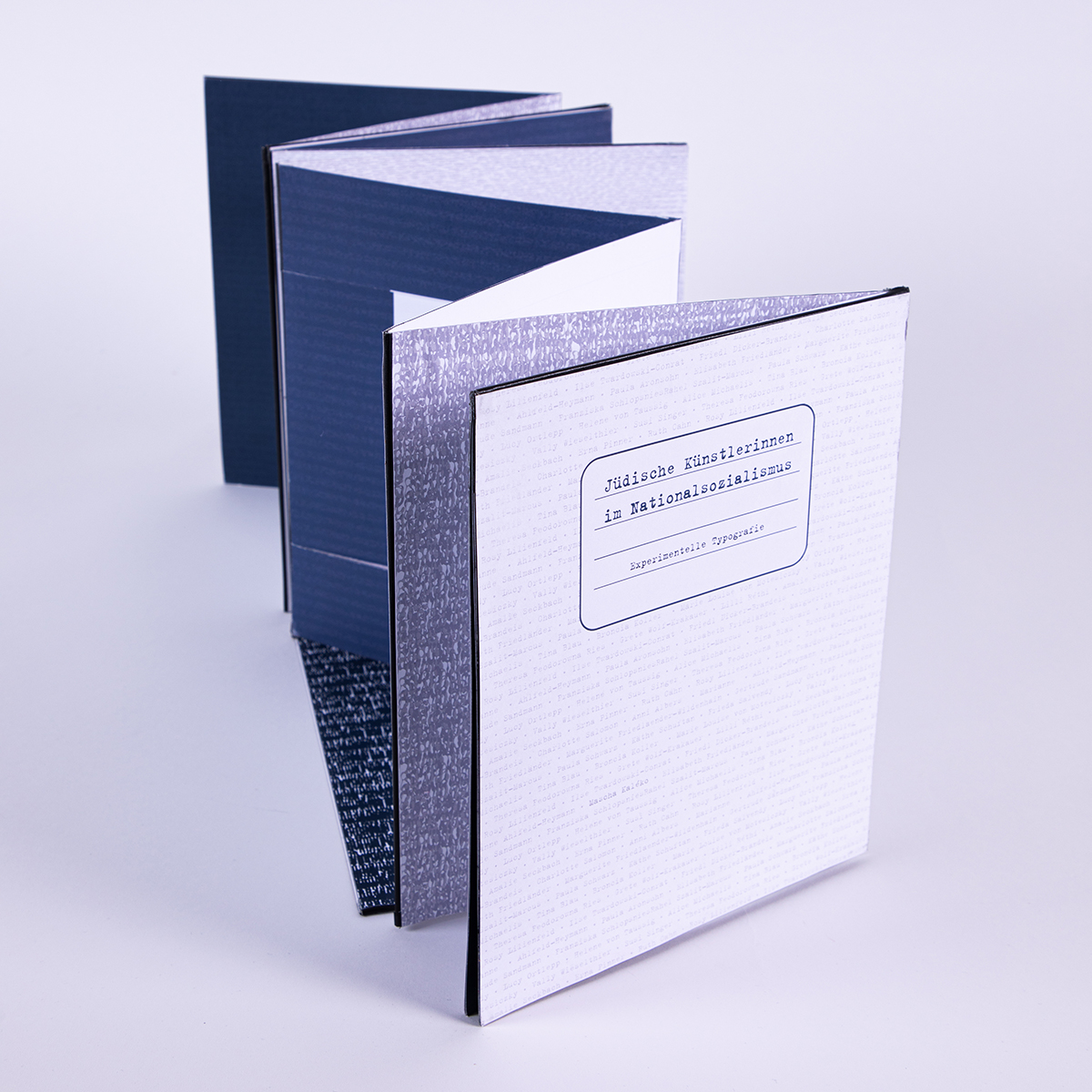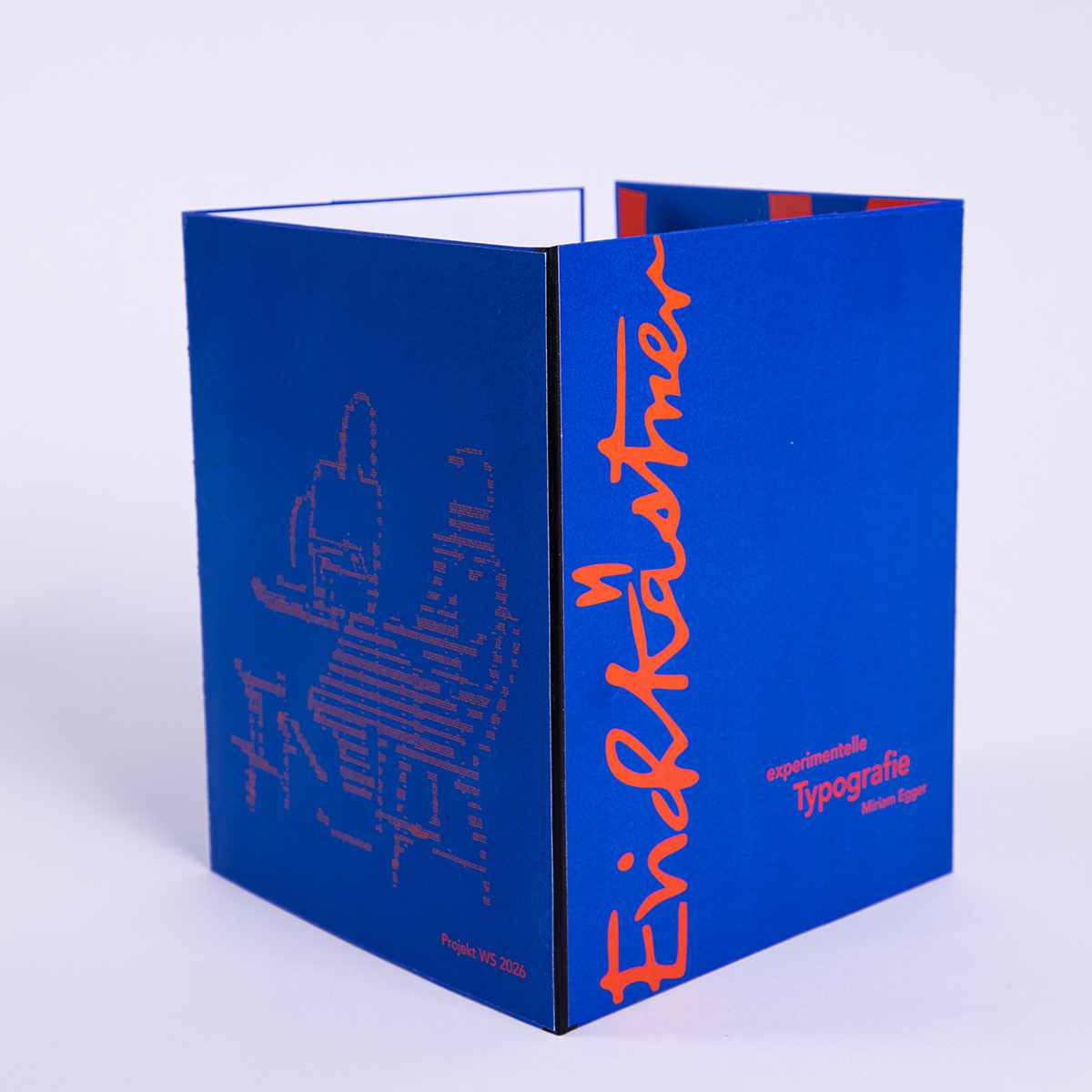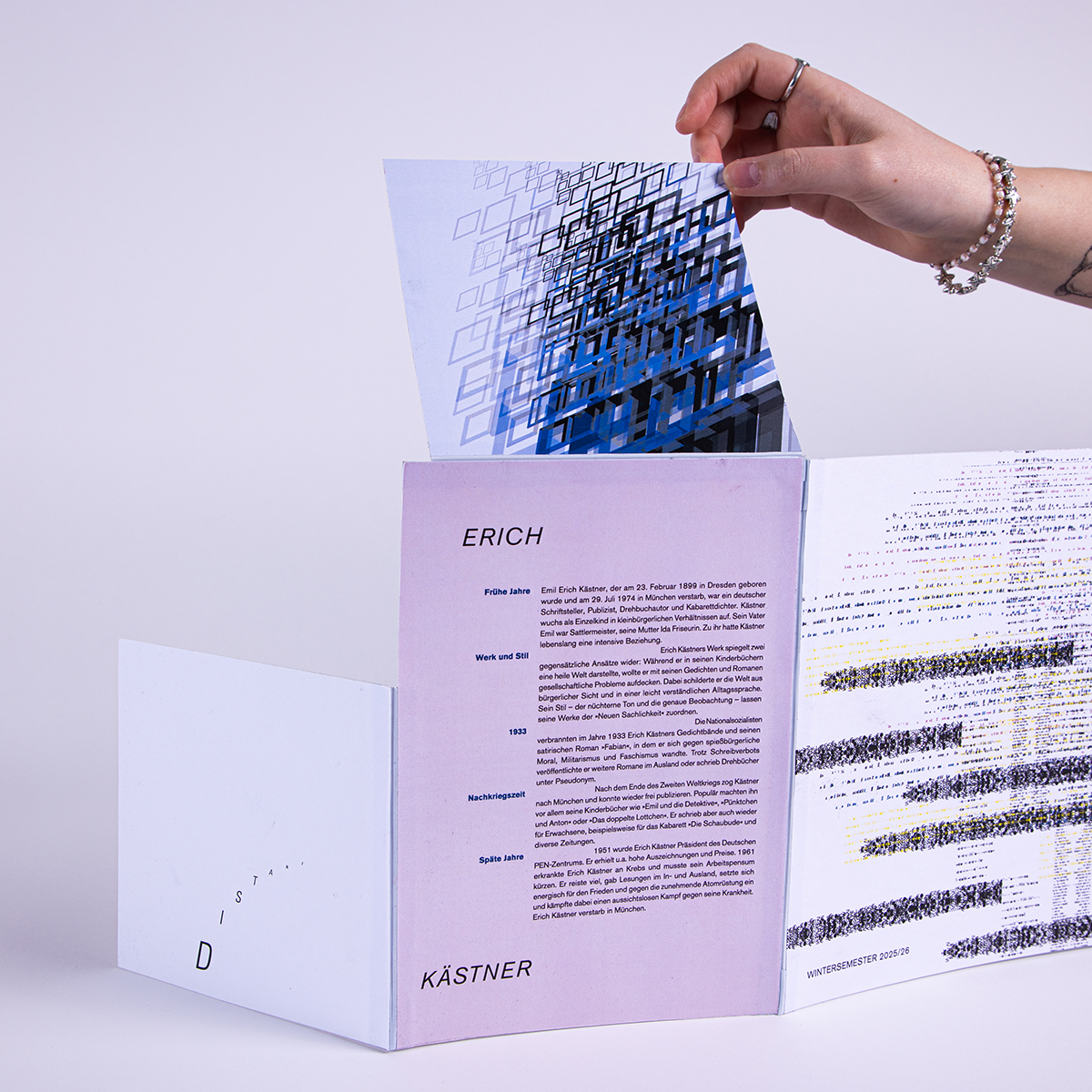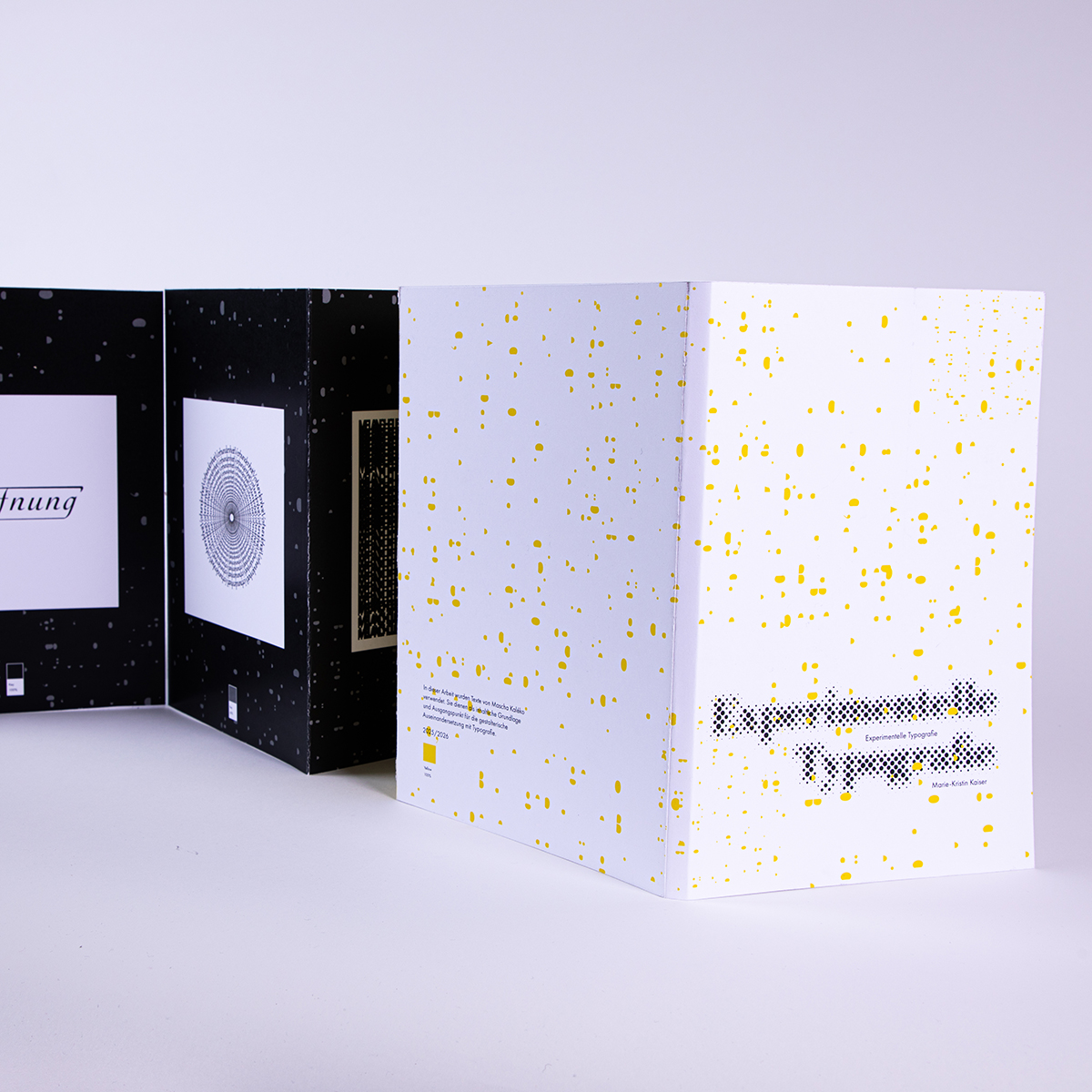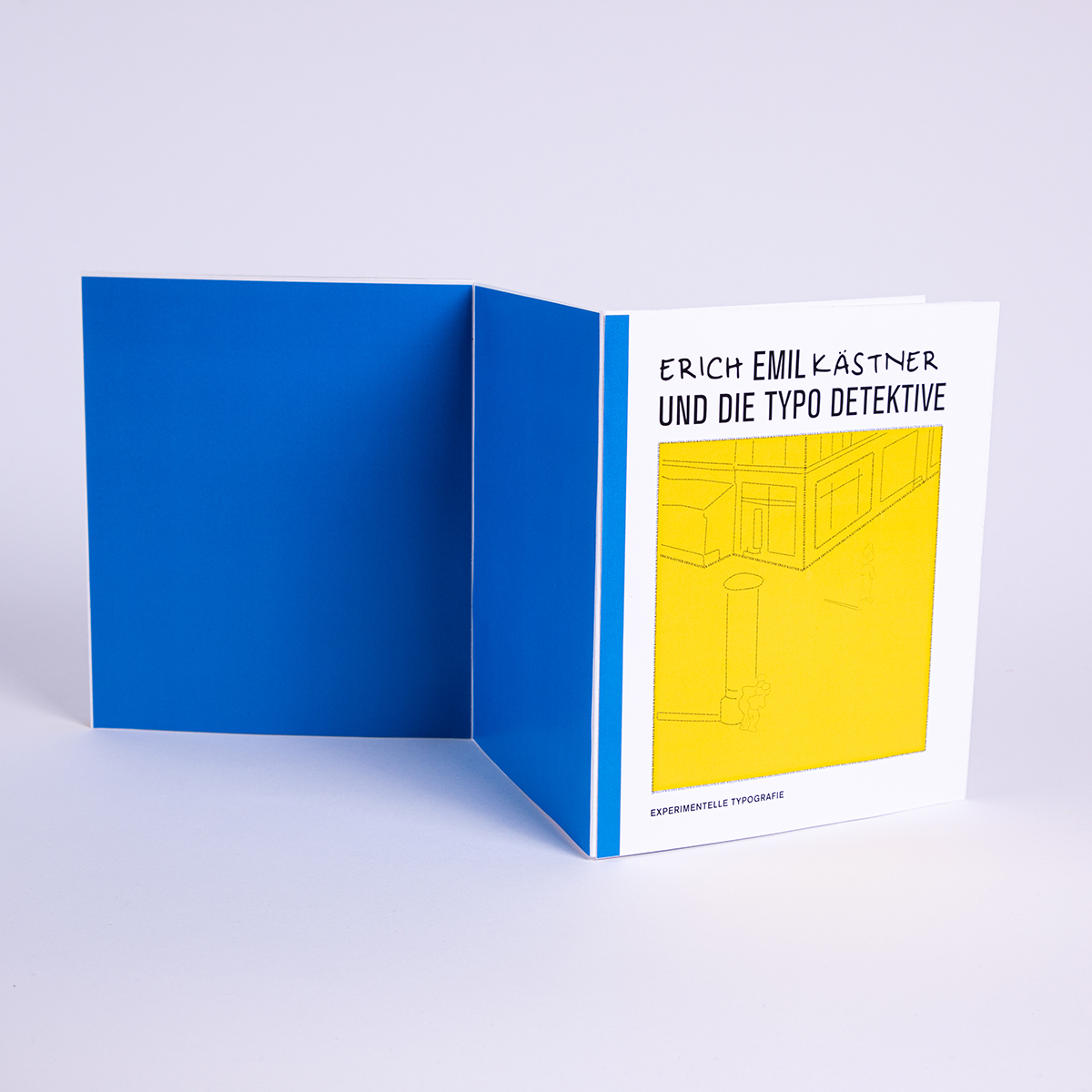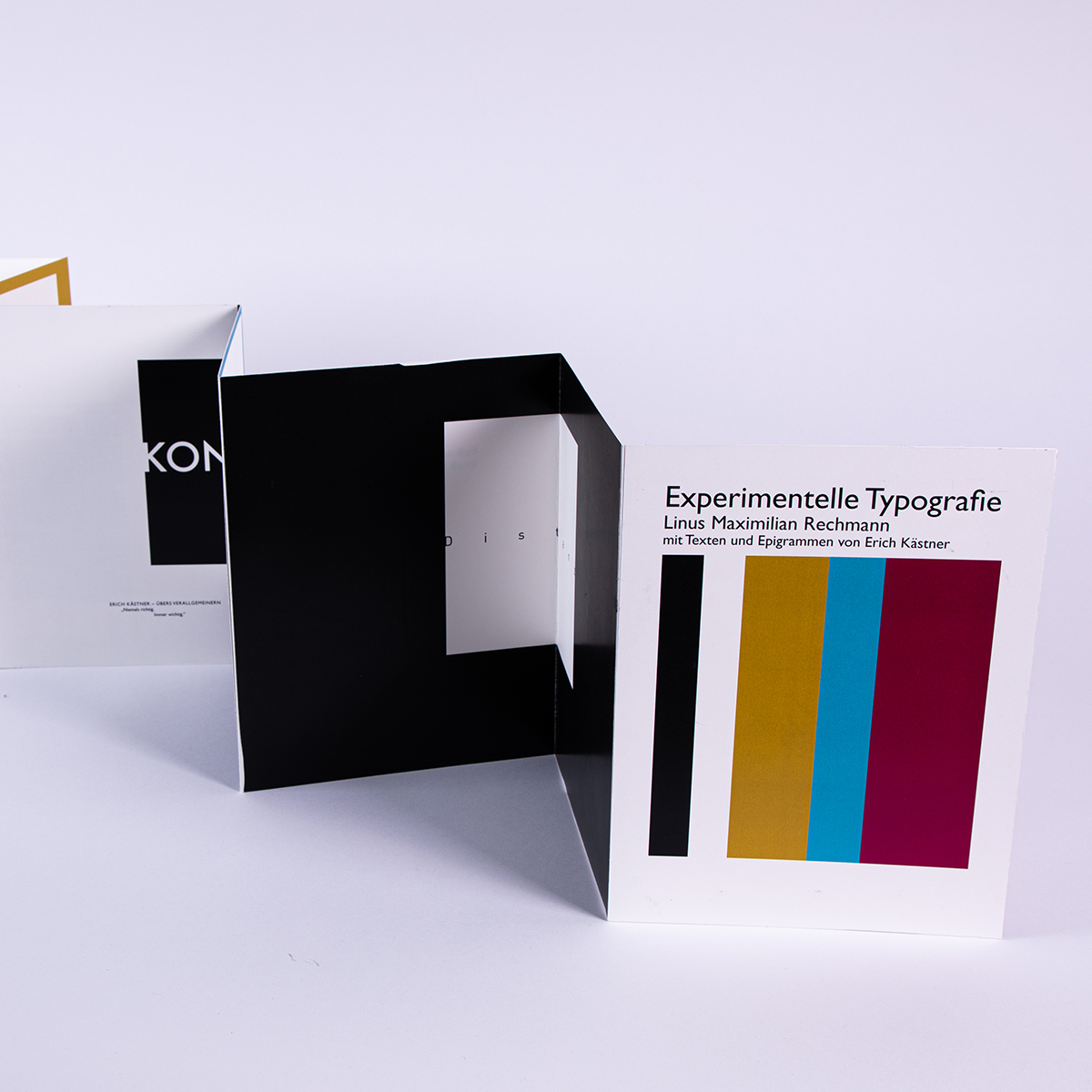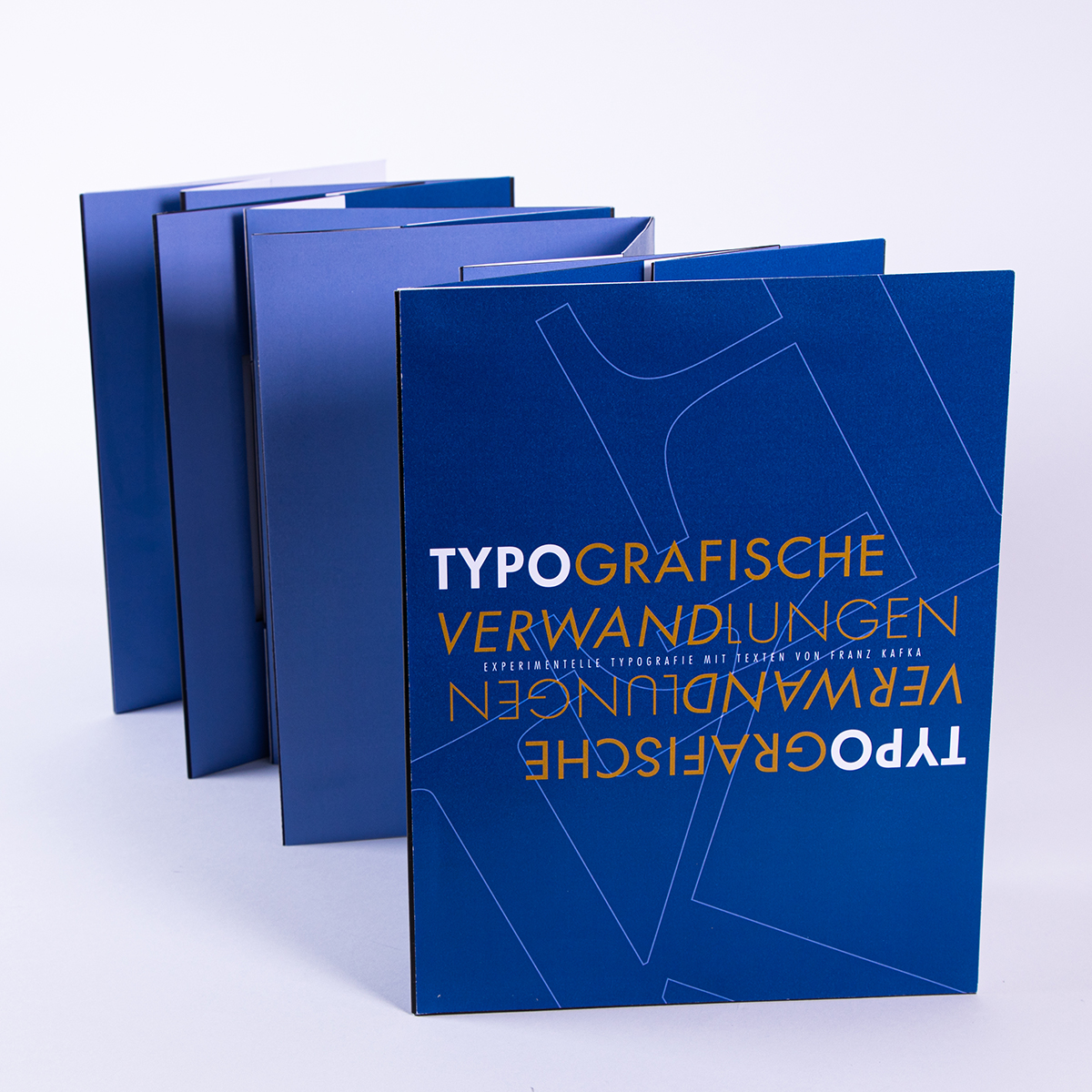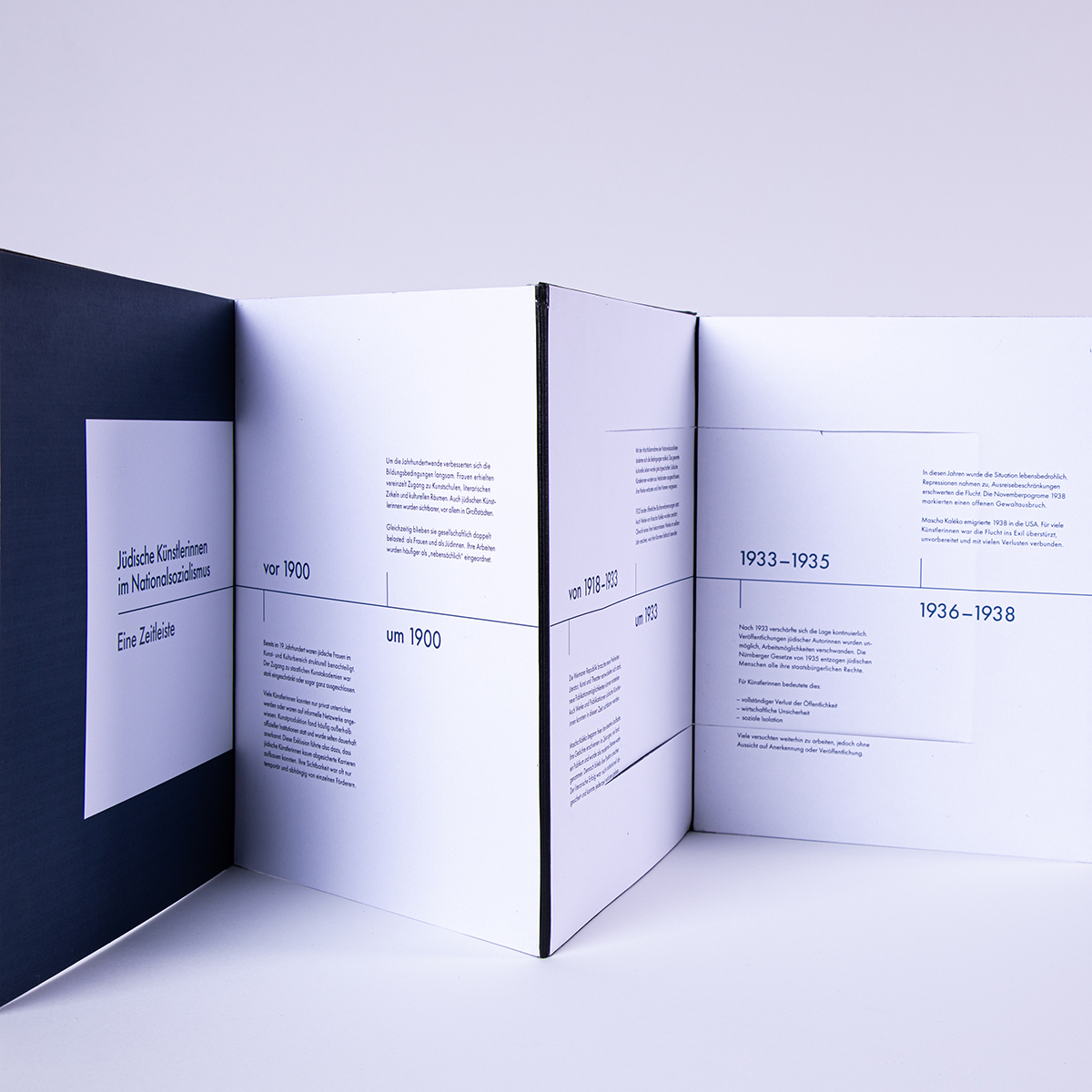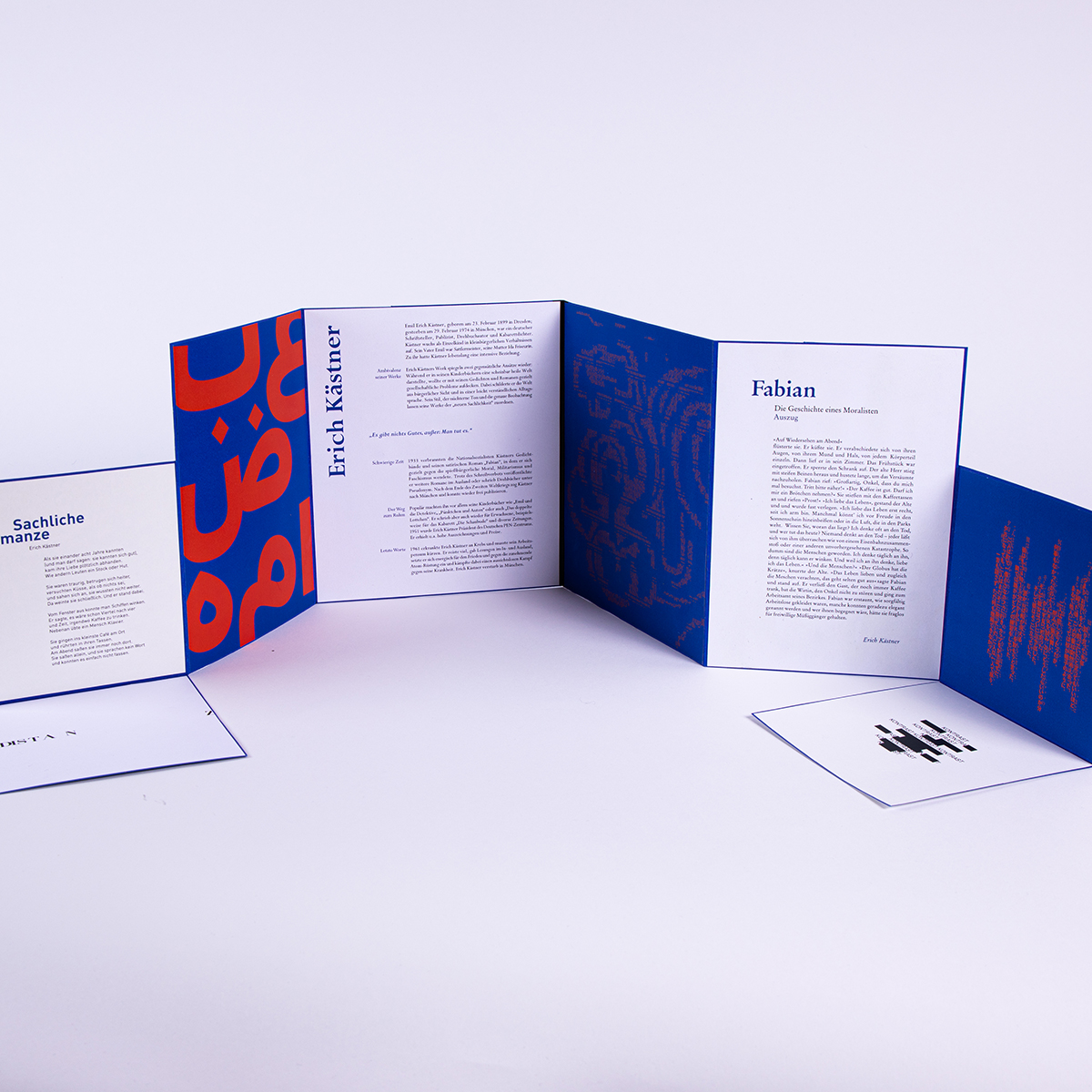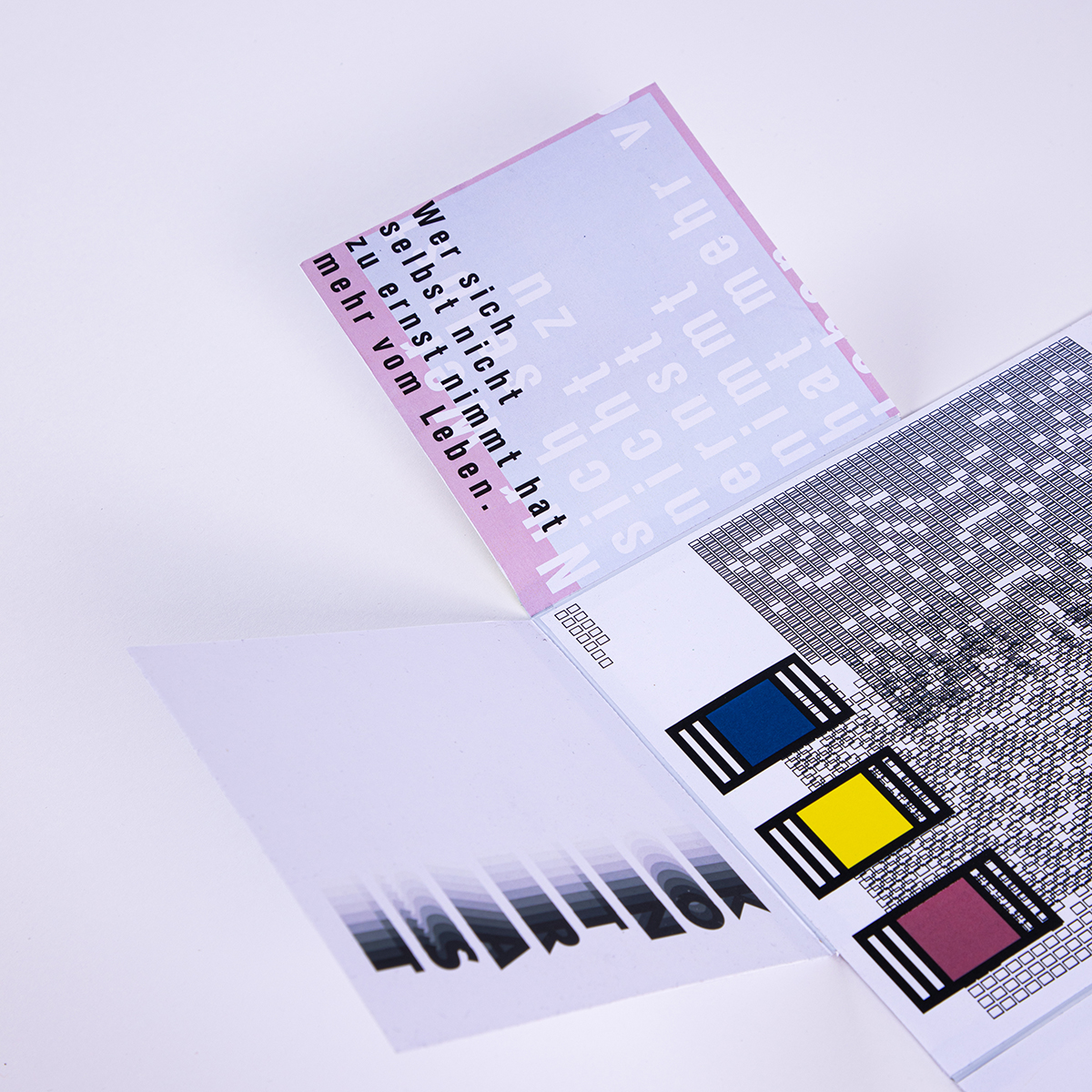
»Experimentelle Typografie«
Grundlagenprojekt
»Experimentelle Typografie«
Dieses Grundlagenprojekt im ersten Semester dient dem spielerischen Erfahren und Erkennen der Regeln von Lesbarkeit und Lesefreundlichkeit.
Anhand von Texten von drei Autor:innen – Mascha Kaléko, Franz Kafka und Erich Kästner –, die in diesem Jahr zur Auswahl standen, wurden Faltobjekte gestaltet, die sich sowohl im Bereich des Lesbaren als auch des Unleserlichen bewegten.
Dabei galt es, ein Gedicht, einen literarischen Text sowie einen Lexikoneintrag rein typografisch interessant und inhaltlich so leicht erfassbar wie möglich zu gestalten – und im Gegensatz dazu auch Layouts zu kreieren, die als komplett unleserlich zu bewerten sind.
Anbei sind Arbeitsbeispiele von sieben Studierenden abgebildet.